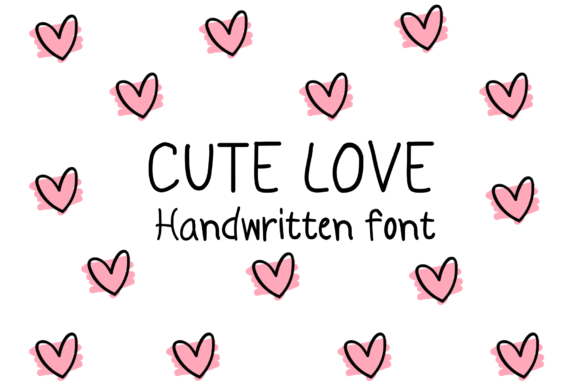
Cute Love
Việc tìm kiếm các thành phần thiết kế phù hợp có thể là một thách thức, nhưng Cute Love cung cấp một bộ sưu tập đặc biệt giúp nâng tầm công việc của bạn ngay lập tức.
Cho dù bạn đang tạo sản phẩm POD (In theo yêu cầu), thiệp mời đám cưới hay đồ họa mạng xã hội, Cute Love đều là một sự lựa chọn lý tưởng.